在黑板报和会场布置中,经常会使用到艺术字体,它也是商品包装的热衷方法,目前各种明艺术字体被大众逐渐接受并喜欢,甚至在报刊杂志和装潢以及个人的签名展示中也开始被大量使用,那么如何让上千万的汉字进行字体的加工?义启字库为您解答。
艺术字体主题有多种类型,字体内部的变化要顺应设计关系,建立两者之间的连接,之所以可以连,是因为它们是比较接近的,连起来是不违背美感的,是顺应笔画的,保证了识别性的前提之下,可以通过不同的横竖的连接画隔断,还有线条从头到尾的连贯性,要充分观察和利用字体内部的变化关系,使其整体比较凝练,或者是其他线条进行勾勒,就像画草图一样,这样进行真正的设计时思路会更加清晰。
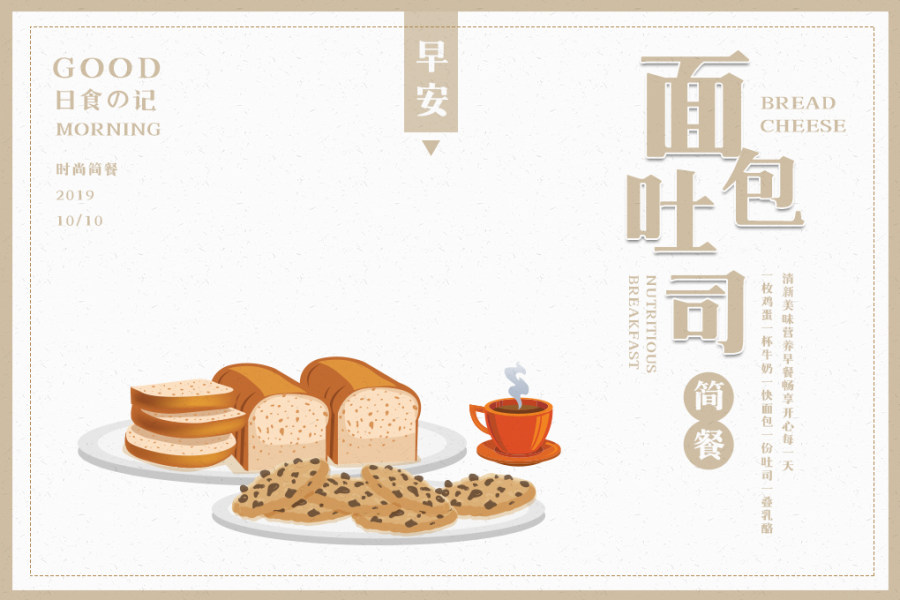
艺术字体设计加工就是在做细节,因为细节的变化,使各个艺术字里互相呼应,它能形成一种艺术字设计的整体美感:如以简单的横线来讲,不同的横线端点的处理形式不同。比如在艺术字的右侧进行盲点的改变和调整,只需要直接选择工具,把右下角的端点往里拖,通过转换盲点就可以变成曲线,但要根据不同的艺术字主题、不同的设计环境和要求来进行实际改造。
各位一定要根据字体的体系设计艺术字体,详细的解读字体文件,艺术字是普通的中规中矩汉字的有效补充,但是它们二者有着本质上的区别,艺术字除了信息的交流以外,更重要的是展示特色,形成独特的字体体系,所以工作量巨大。